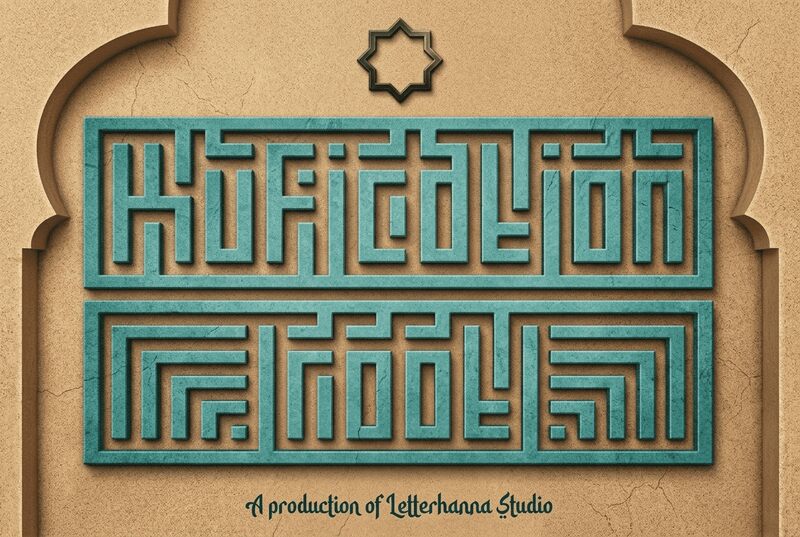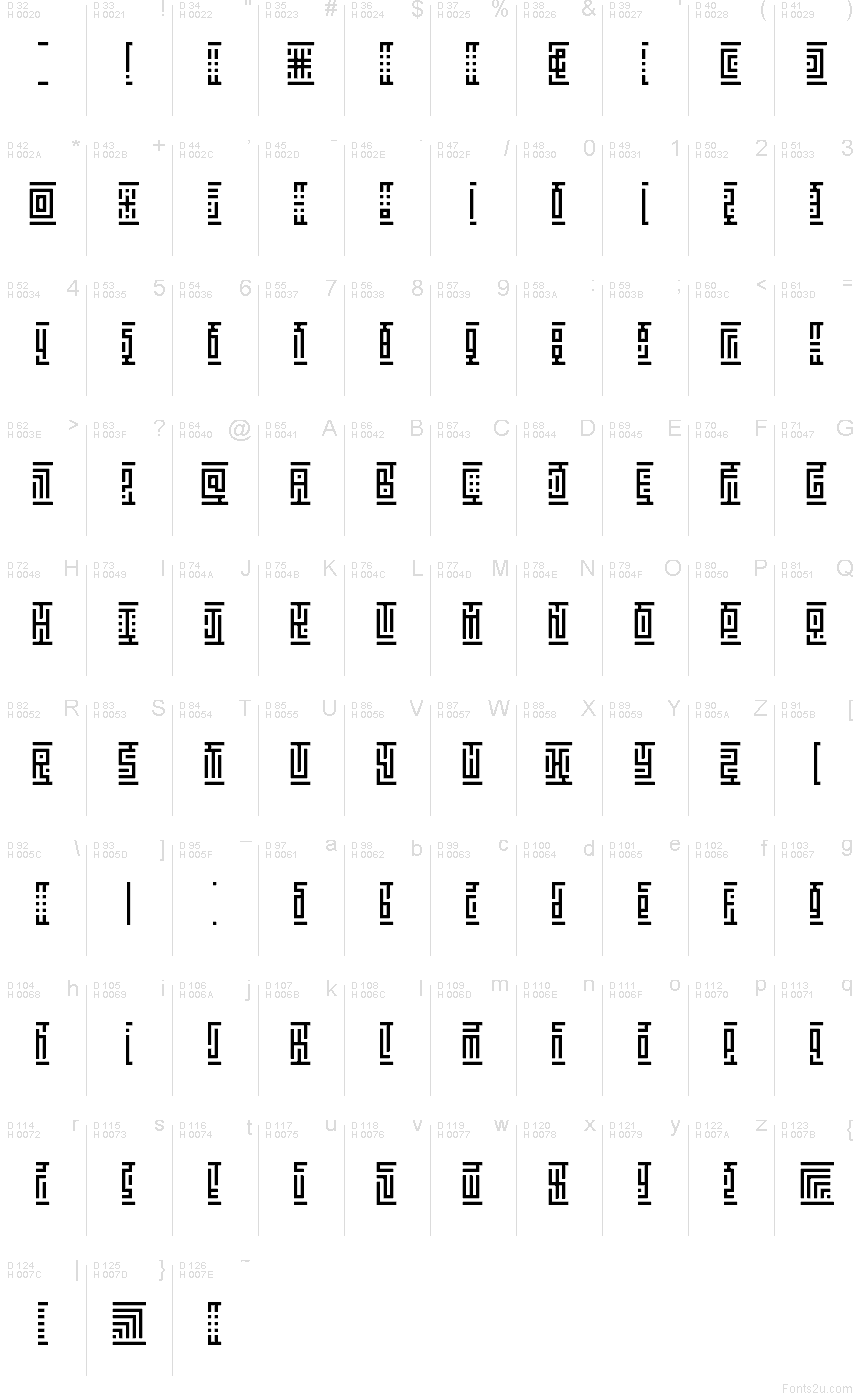
Kufication Root von Rinaldo Hasibuan ist eine kostenlose, vom Kufi inspirierte Display-Schrift mit strengem, geometrischem Rhythmus und einer labyrinthartigen Silhouette. Die Buchstaben fügen sich in rechtwinklige Drehungen, lange Vertikalen und flache Balken ein, was der Schrift eine architektonische Anmutung verleiht – fast wie ein modulares Schriftbild aus einem Guss.
Ideal für Plakattitel, Musik-Cover, Streetwear-Branding, Logo-Entwürfe, Titelkarten und Monogramme, bei denen die kompakten, ineinandergreifenden Formen wirken. Als Free Font entfaltet sie ihre Stärke vor allem in kurzen Display-Anwendungen, da die wiederkehrenden rechten Winkel selbst wenigen Buchstaben einen starken grafischen Charakter verleihen.